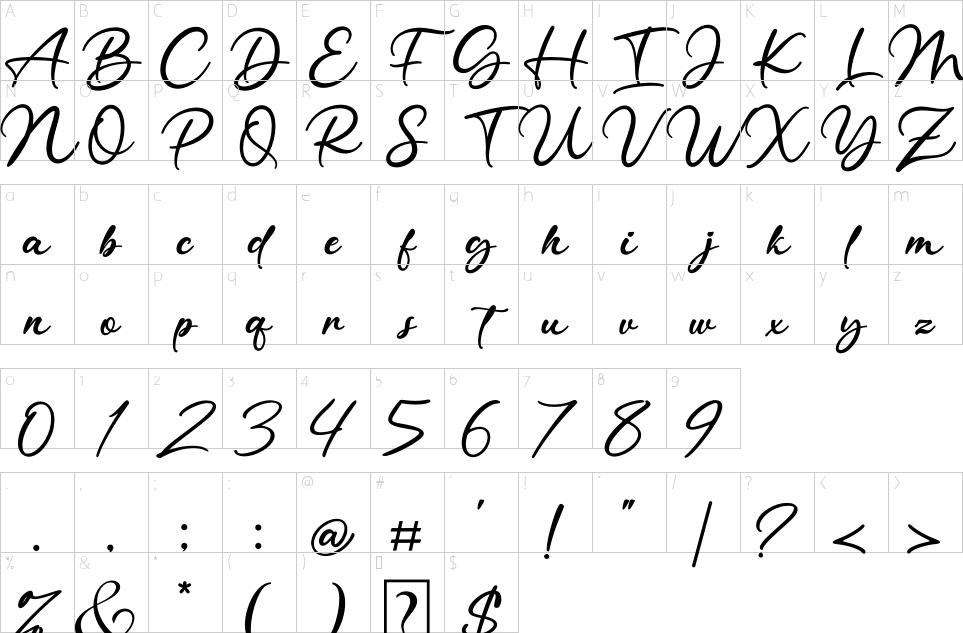
A fonte Andalugia é uma opção perfeita para designers e profissionais de design gráfico que buscam uma fonte com um toque elegante e versátil. Desenhada pelo estúdio Basnistudio, ela oferece um estilo único que pode trazer uma resolução interessante a qualquer projeto. Seu design foi projetado para ser tanto funcional quanto estiloso, permitindo que você personalize seu design de acordo com as necessidades específicas do seu projeto. Desenvolvida para Windows e Mac, Andalugia é uma escolha ideal para quem procura uma fonte sem custos, que proporciona a qualidade de design que você merece sem comprometer seu orçamento. Até o momento, a fonte foi baixada 295 vezes, demonstrando a sua popularidade e qualidade. Se você está procurando por uma fonte para seu próximo projeto, Andalugia pode ser uma excelente escolha.